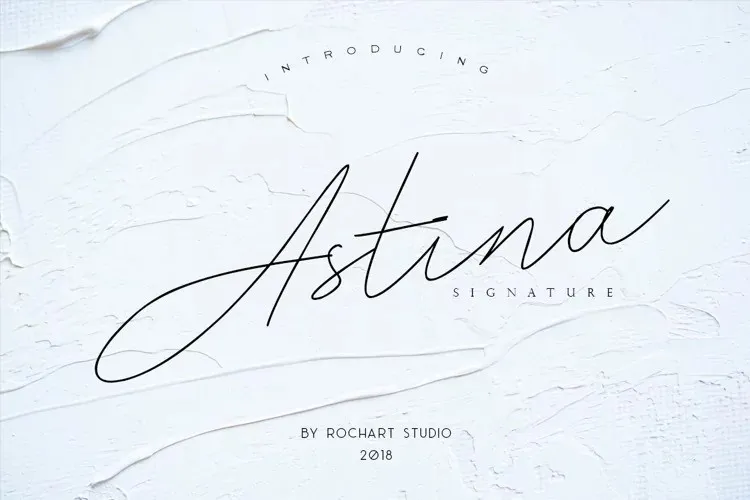
Astina Font – Fonte Grátis
Astina Font
A Astroina Font é uma elegante tipografia escrita a mão, com características orgânicas que criam um estilo fresco e vibrante. Este tipo abrange não apenas ligaturas adicionais para maior flexibilidade, mas também fornece uma ferramenta perfeita para artistas digitais, designers de logos, criação de marcas e design de materiais impressos. Seja você um artista digital buscando criar designs de arte de letras, uma empresa que está em busca de uma identidade visual única ou até mesmo quem precisa de uma mão cheia nas criações da sua próxima peça publicitária, a Astroina tem o poder para atender suas necessidades. Especialmente adequada para uso em logos, marcas e design digital, a Astroina também é ótima para aplicações mais tradicionais como signos e propaganda, bem como t-shirts e roupas de designer. Este tipo suporta todos esses formatos de criação artística, garantindo que você tenha o poder de expressar seu estilo pessoal em qualquer formato.